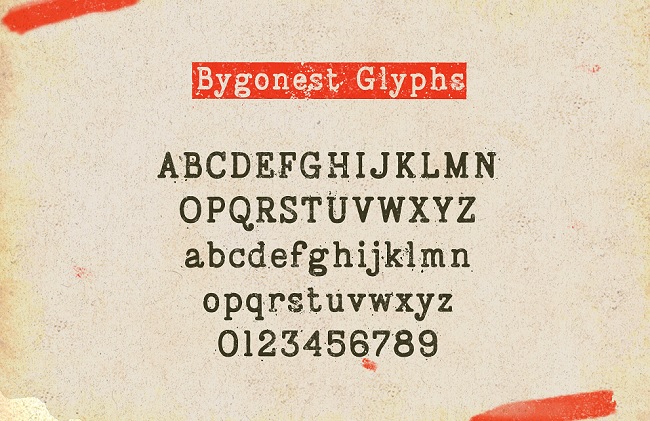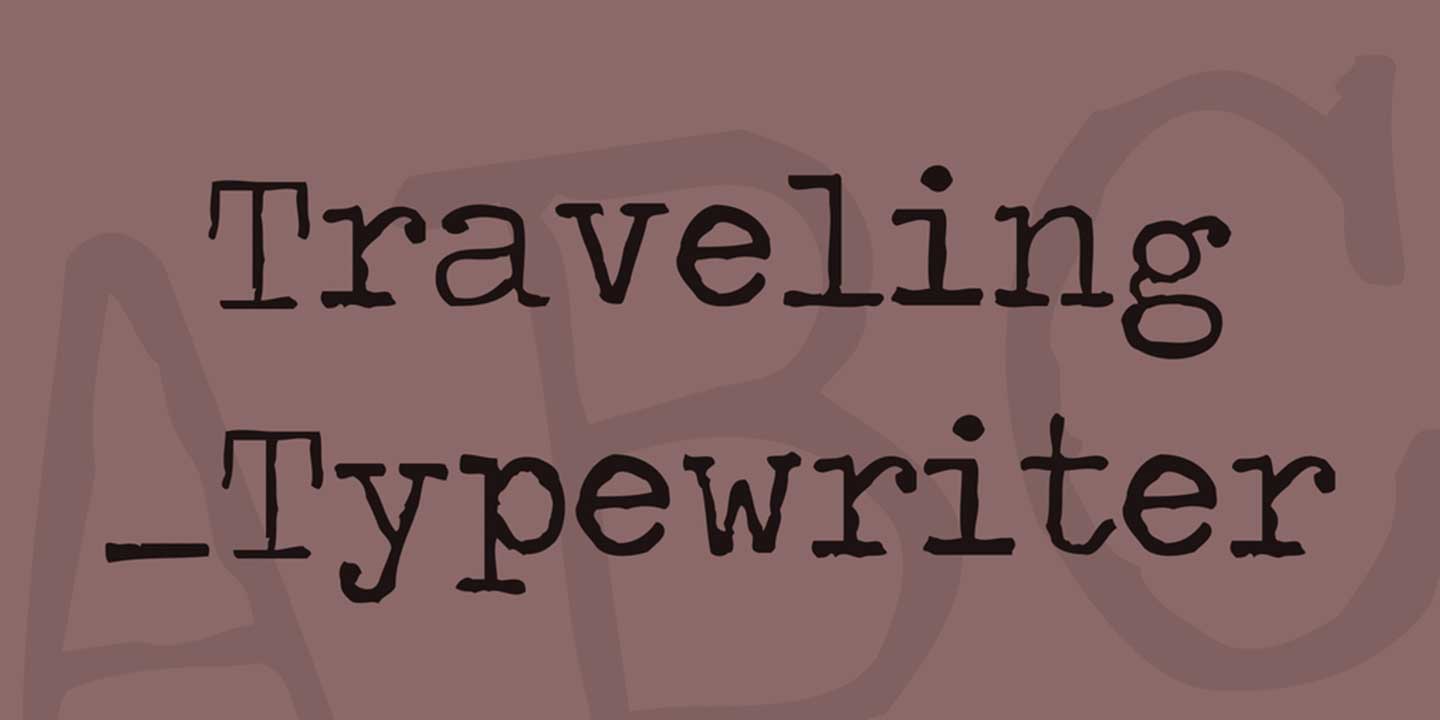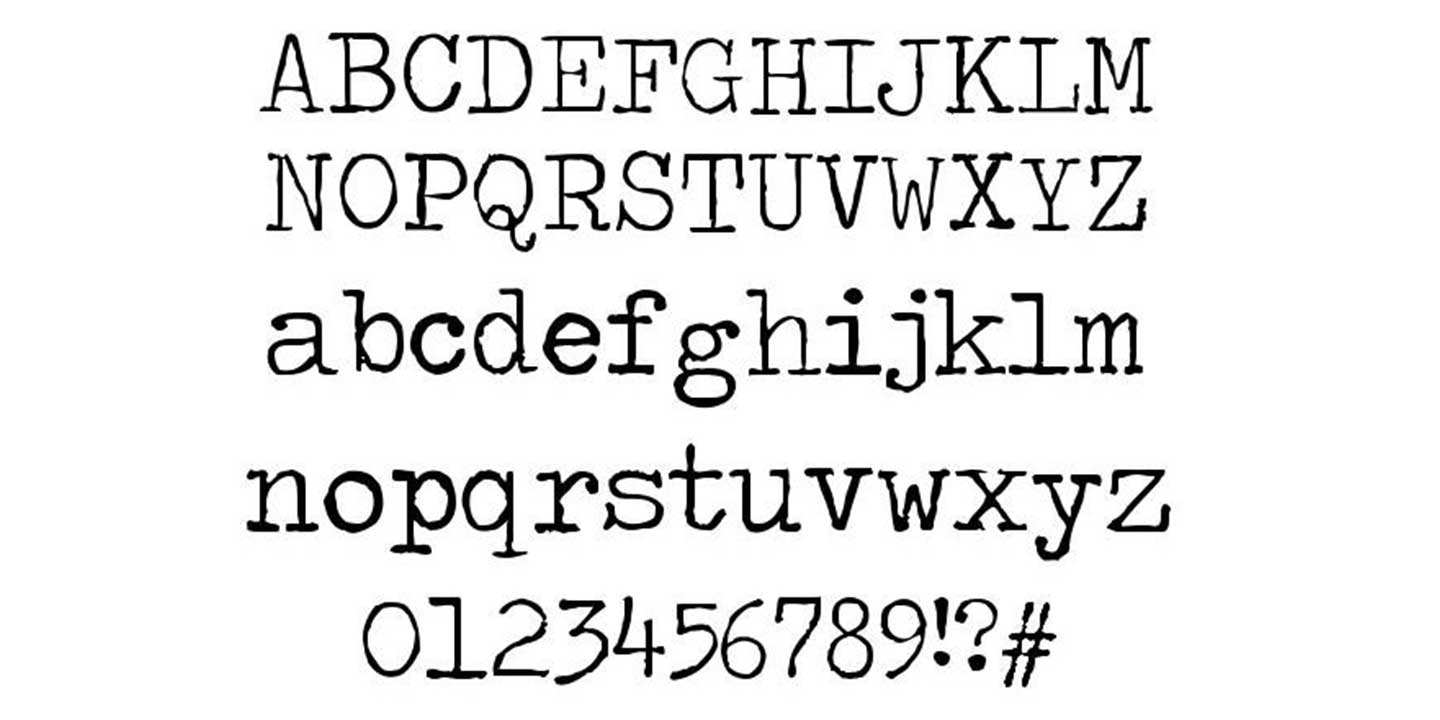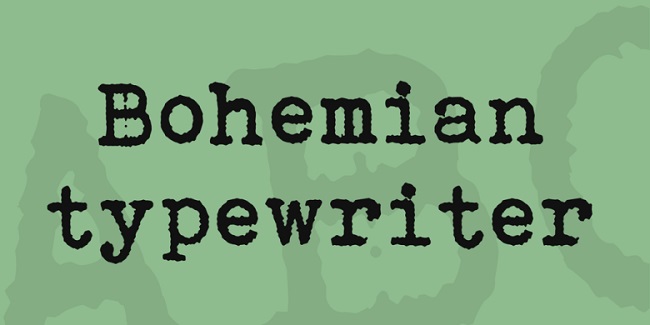
Font Typewriter Việt hóa – Tải font chữ máy đánh chữ cổ điển và độc đáo
Font Typewriter Việt hóa là bộ sưu tập các phông chữ mô phỏng lại hoàn hảo ký tự cơ học từ những chiếc máy đánh chữ truyền thống. Với diện mạo thô mộc, có chút không hoàn hảo nhưng đầy tính hoài niệm, nhóm phông chữ này là lựa chọn hàng đầu cho các thiết kế mang phong cách Vintage, bưu phẩm cổ điển, nhãn dán sản phẩm thủ công và bao bì cà phê mộc. Doozypack.vn cung cấp link tải trọn bộ font chữ đánh máy ngày xưa chuẩn kỹ thuật, giúp bạn sở hữu kho phông chữ hoài cổ độc đáo, hỗ trợ tiếng Việt mượt mà để hiện thực hóa mọi ý tưởng thiết kế phá cách.
Đặc điểm thẩm mỹ độc đáo của bộ font Typewriter
Phông chữ máy đánh chữ không đi theo sự bóng bẩy của các định dạng kỹ thuật số hiện đại; nó mang đến một ngôn ngữ thị giác đầy tính tự sự, gợi nhắc đến những tài liệu mật và những bức thư tay của thế kỷ trước.
Mẫu chữ phong cách máy đánh chữ
Phong cách máy đánh chữ cơ học gợi nhớ thập niên trước
Đặc trưng lớn nhất của Font Typewriter Việt hóa là sự không hoàn hảo mang tính cơ học. Các ký tự mô phỏng lực gõ của các thanh gõ (typebars) lên dải băng mực, tạo ra những nét đậm nhạt ngẫu hứng hoặc hiệu ứng lem mực nhẹ quanh biên chữ. Chi tiết hoài cổ này mang lại cảm giác chân thực, ấm áp và rất có chiều sâu lịch sử khi ứng dụng vào thiết kế bao bì sản phẩm.
Cấu trúc đơn cách (Monospaced) minh bạch và thô mộc
Hầu hết các bộ font chữ đánh máy ngày xưa đều sở hữu cấu trúc Monospaced (đơn cách), nơi mọi ký tự chiếm một khoảng không gian chiều ngang hoàn toàn bằng nhau. Sự đều đặn một cách cơ học này tạo nên một nhịp điệu Typography vô cùng ngăn nắp, mộc mạc và rất dễ đọc trên các nhãn dán thông tin kỹ thuật hoặc tem niêm phong hộp quà.
Ưu điểm nổi bật của bản Font Typewriter Việt hóa
Khi ứng dụng các phông chữ đánh máy quốc tế vào thị trường trong nước, sự chỉn chu về dấu câu là yếu tố quyết định đến tính chuyên nghiệp của bản thiết kế:
• Khắc phục triệt để lỗi dấu tiếng Việt: Phiên bản Việt hóa đã được đội ngũ thiết kế trau chuốt thủ công từng dấu câu. Các dấu sắc, huyền, hỏi, ngã, nặng được vẽ đồng điệu với cấu trúc cơ học của thân chữ, không gây cảm giác chắp vá hay làm mất đi tính nguyên bản của font.
• Bảo đảm tính đồng nhất thương hiệu: Việc sử dụng bản font chuẩn giúp bạn tự tin dàn trang tiêu đề tiếng Việt mà không lo hiện tượng lỗi ô vuông hay nhảy về font hệ thống khô khan.
Kiểu chữ typewriter cổ điển
• Tem mã vạch & Lô sản xuất (Batch Code): Cấu trúc đơn cách chuẩn xác rất phù hợp để in ấn các dãy số serial, ngày sản xuất trên tem decal dán bao bì công nghiệp.
Thiết kế typography hoài cổ
Lưu ý kỹ thuật khi in ấn với phông chữ máy đánh chữ cổ điển
Việc sản xuất bao bì thực tế sử dụng các phông chữ mang dấu ấn cơ học đòi hỏi sự am hiểu kỹ thuật chuyên sâu tại xưởng in Doozypack.vn:
• Kiểm soát hiện tượng tràn mực (Dot Gain): Các nét chữ của Typewriter có độ dày vừa phải nhưng cấu trúc đơn cách tạo ra nhiều khoảng trống. Trên giấy Kraft thô nhám, hãy đảm bảo size chữ tối thiểu từ 8pt trở lên để thông tin luôn rõ ràng.
• Hệ màu CMYK cho văn bản: Luôn thiết kế trên hệ màu CMYK và đặt màu đen cho văn bản ở thông số K=100 đơn sắc để chữ sắc nét nhất, tránh hiện tượng nhòe màu do lé bản kẽm khi in chồng nhiều màu.
• Quy tắc Convert Font bắt buộc: Trước khi gửi file in PDF cuối cùng đến Doozypack.vn, hãy luôn thực hiện lệnh Create Outlines (Ctrl+Shift+O) cho toàn bộ văn bản để tránh tình trạng máy in của xưởng bị thiếu font gây lỗi nhảy chữ.